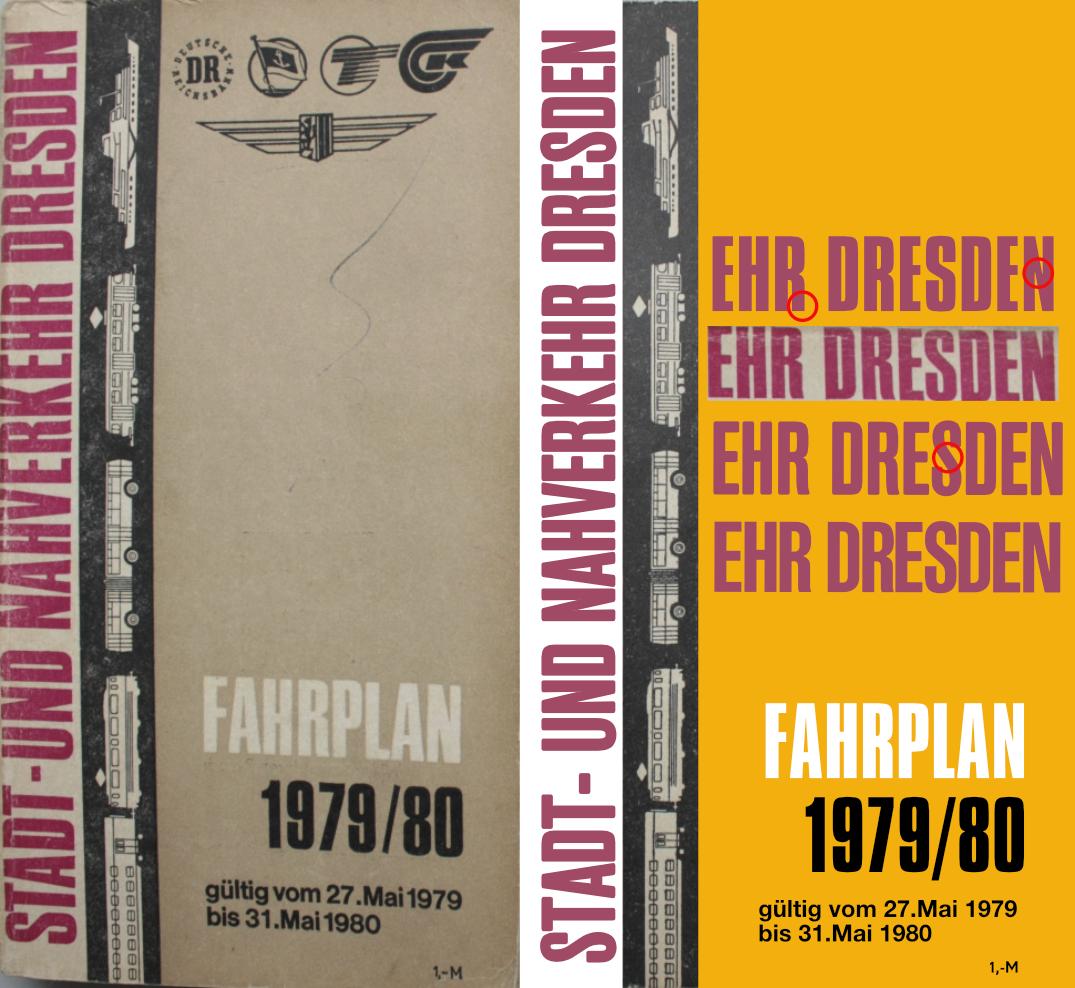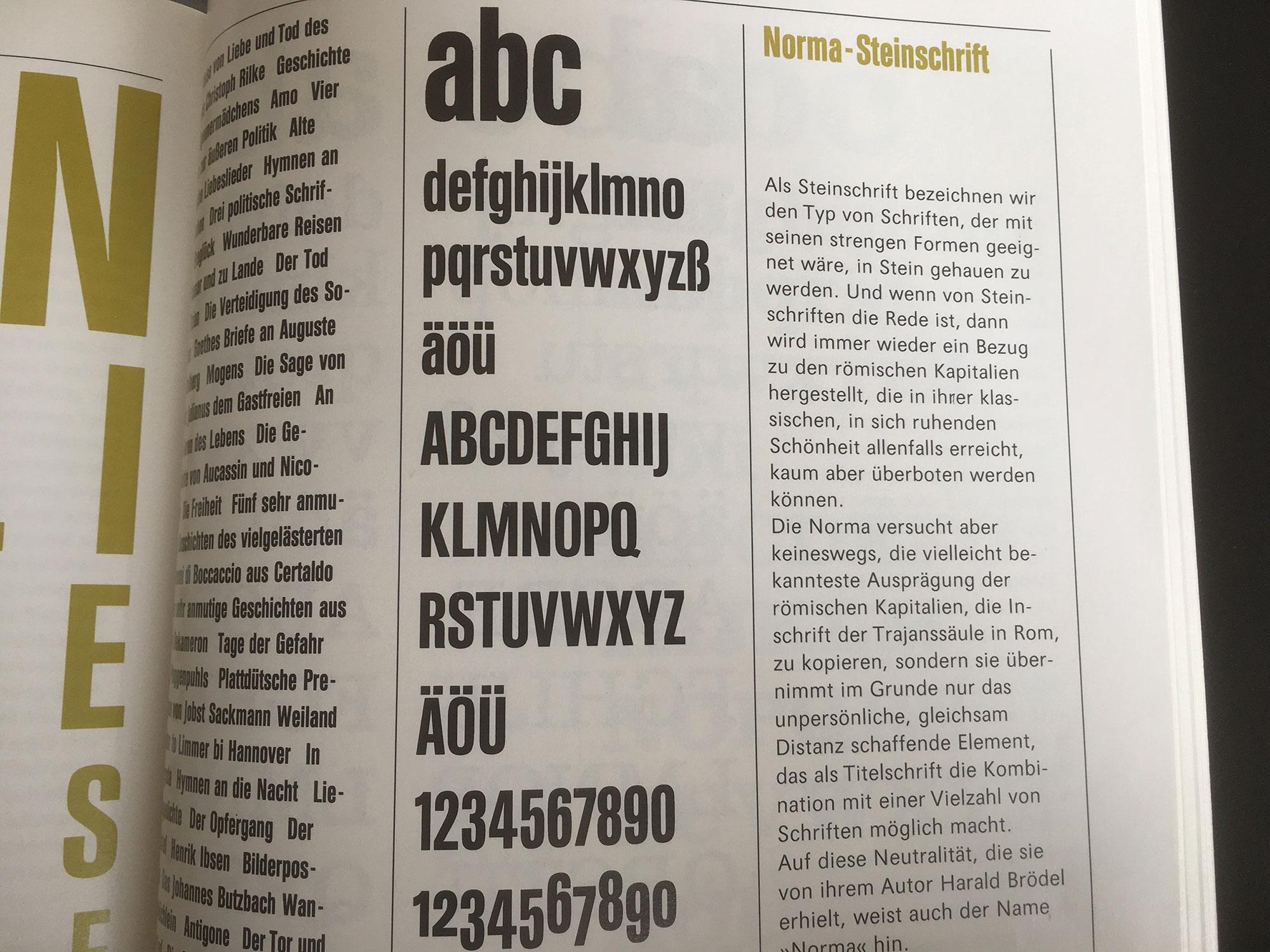
Suche Schriftart von Fahrplanheft Dresden
ich bin auf der Suche nach der Schriftart, welche für "Stadt- und Nahverkehr Dresden" verwendet wurde. Bis zur letzten Ausgabe 1991/92 hat sich das Titelblatt (bis auf die Symbole der Verkehrsträger) nicht geändert.
Ich bin bereits auf die Steinschrift Pro bzw die Akzidenz Grotesk Medium gekommen. Leider entspricht nur die Compacta fast diesem Textteil. Im Detail jedoch ergeben sich Unterschiede (R, S). Kann jemand helfen?
Hallo, diese Schrift ist aus der Zeit als es noch Bleisatz gab. Man könnte bei Linotype Glück haben, daß es dort noch Schriftmuster gibt.
Zu dieser Zeit gab es zwar noch den Bleisatz, aber es gab auch Fotosatz.
Ich erinnere mich, dass ich damals selbst Schriftschablonen anfertigte. Für Titelsatzgeräte. Ob es „Staromat“ oder ähnliches war, kann ich nicht mehr sagen.
Als Vorlage verwendete ich Letraset Anreibebuchstaben aber wahrscheinlich auch Barythabzüge. Kann ich ebenfalls nicht mehr mit Bestimmtheit sagen.
Jedenfalls haben auch Satzstudios Schriftschablonen manchmal selbst hergestellt.
Könnte mir nun vorstellen, dass jemand mit bestimmten Buchstaben der gewählten Schrift nicht einverstanden war und den jeweiligen Buchstaben aus einer anderen Schrift in die Schablone eingebaut oder modifiziert hat.
Im gezeigten Beispiel kommt mir das so vor, da alles auf „schmalfette Akzidenz Grotesk“ hinweist. Hingegen einige Buchstaben auf „schmalhalbfettte Akzidenz Grotesk“ oder eine andere Schrift.
Die beiden „S“ z. B. waren ja im Original unterschiedlich gestaltet. Warum auch immer.
Man bastelte sich die Schrift zurecht.
So hatte man die „schmalfette Akzidenz Grotesk“ wie man sie wollte.
Ist zwar alles nur eine Theorie von mir, könnte aber vielleicht so gewesn sein.
Ein wenig wundere ich mich, dass wir hier bei den Vorschlägen so komplett im NSW unterwegs sind, rein von der zeitlichen Einordnung der gesuchten Vorlage. Gab es da nichts beim Typoart?
Dachte es könnte die Helvetica Ultra Compressed sein, aber die Fette stimmt nicht wirklich.
Was sind denn deine Beispiele auf dem gelben Grund von oben nach unten? Ganz oben Compacta?
Ja, die Compacta ist die meine ganz oben. Ich weiß nur nicht, ob diese damals auch verwendet wurde bzw als Bleisatz in den 70ern verfügbar war.
Könnte die Schmalfette Grotesk von Walter Haettenschweiler sein. Eine digitale Interpretation ist z. B. die Haettenschweiler von Microsoft. (»I never received a single cent, but at least they named it after me«)
Vielen Dank. Ich probiere es mal aus. Nur die Ziffer "5" hat oben einen schrägen Anschnitt. Zum Vergleich fehlt mir ein Beispiel des Fahrplanes mit einer 5 in der Jahreszahl.
Davon gehe ich aus, wenn man das Land und das Jahr bedenkt.
So ist es nicht.
☞ Norma-Steinschrift
Vielen Dank. Das Buch (im Schuber) habe ich auch im Schrank, aber gar nicht daran gedacht. Nach meinen Recherchen hat es die Norma nicht in die Digitalisierung Geschäft. Ich werde mich "rantasten"... Danke Ralf
ja, die compacta gibt es seit 1963
Hey, vielen Dank. Ich glaube auch, dass es die Compacta zu sein scheint, obwohl das "R" geschwungen ist. Aber vielleicht gab es bei Typoart die Compacta im Bleisatz - wer weiß. Ich orientiere mich halt an der Zeit und der Analogie, denn Schriftsetzcomputer (oder so ähnlich) hielten erst später in der DDR Einzug.
So hatte man die „schmalfette Akzidenz Grotesk“ wie man sie wollte.
Ist zwar alles nur eine Theorie von mir, könnte aber vielleicht so gewesn sein.
Wie auch immer bei der Dresdner DEWAG man sich da was "zurecht gebastelt" hat, den Fotosatz schließe ich in diesem Falle aus und glaube auch, dass man sich etwas zusammengestellt hat. Vielen Dank für Deine Hilfe.